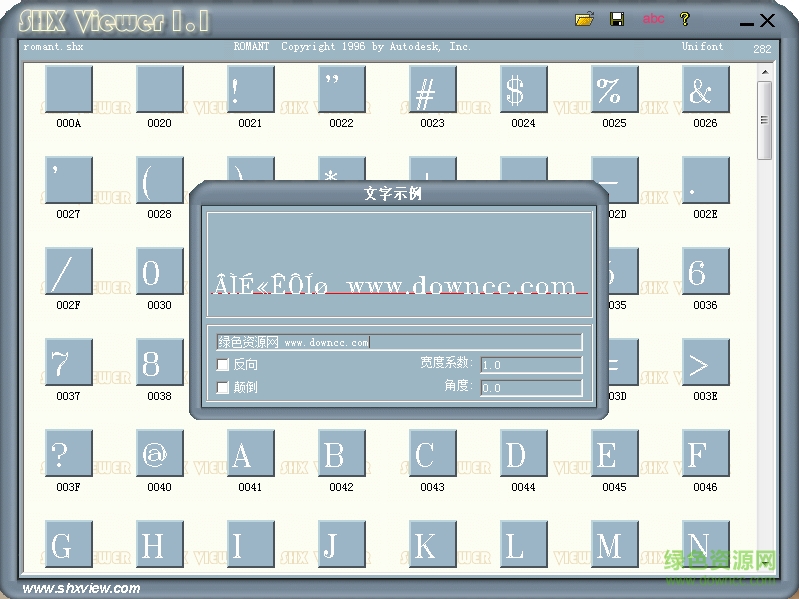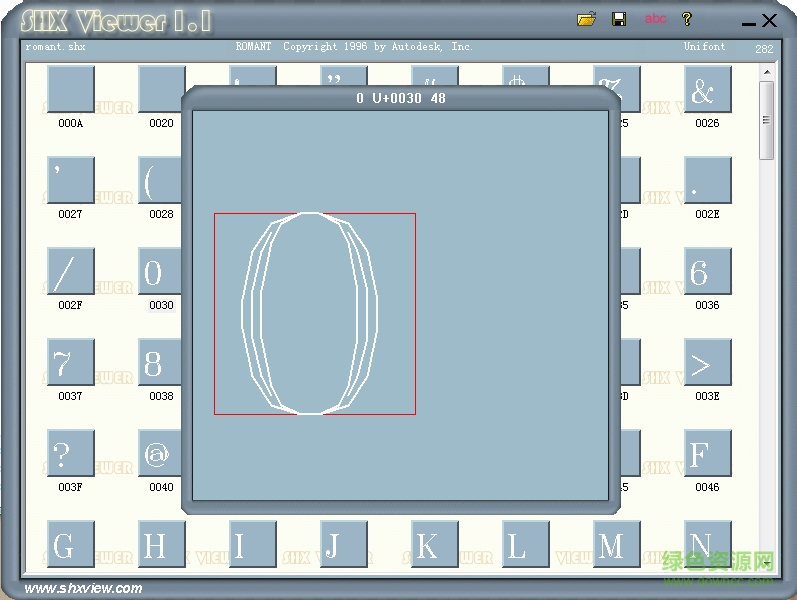
romant.shx是一款為字體增加花邊點綴的cad字體,擁有282個字符,支持字母數(shù)字等,有著舒適的美感,來綠色資源網(wǎng)即可免費下載使用哦!
romant.shx是一個擁有豐富字符的unifont字體,每個字符都用直線修飾,變得更加具有立體感,提供最全的數(shù)字、英文、字符等,可廣泛運營與三維設計、廣告創(chuàng)意、畫圖標注等。